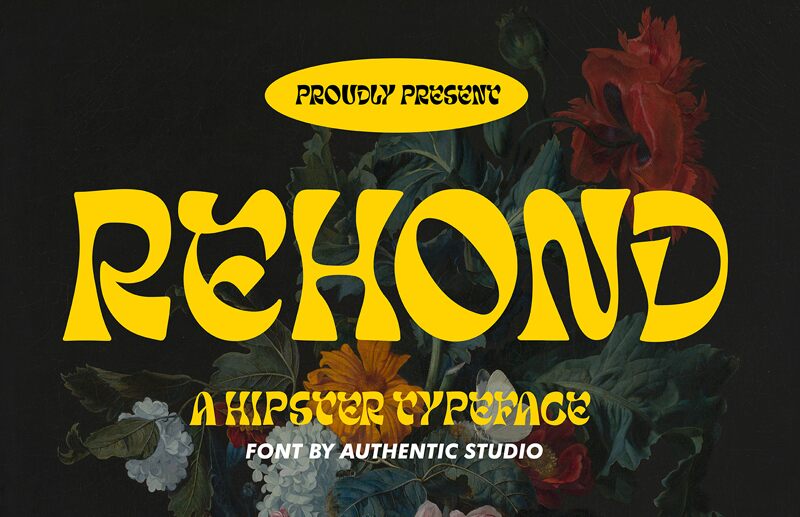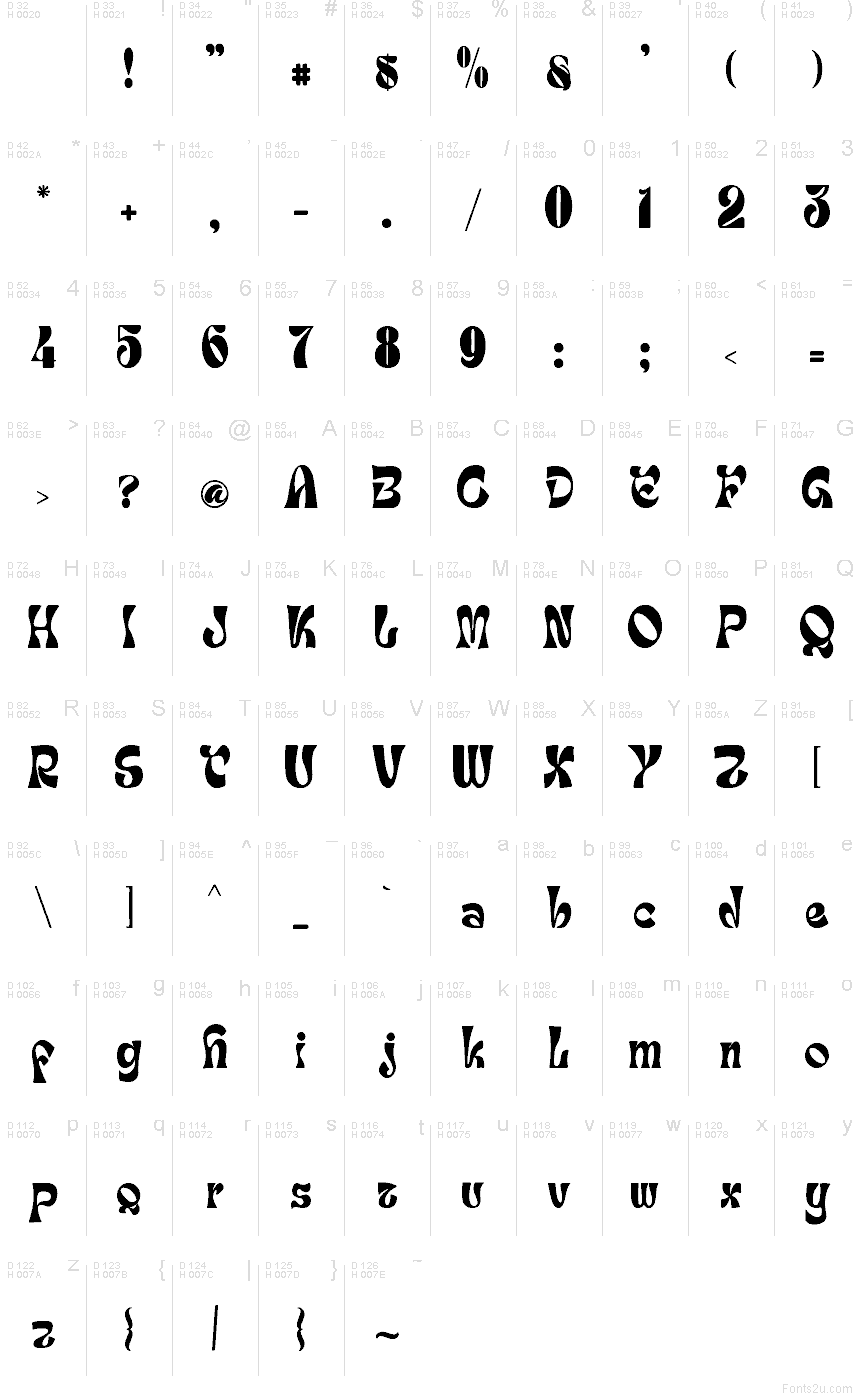
Rehond Font
Rehond Font от Faras Dina — это бесплатный грововый дисплейный шрифт с округлыми, плавными формами и теплым ретро-изгибом в очертании букв. Его формы сочетают в себе мягкие петли, разомкнутые круги и скругленные края, что придает дизайну расслабленный и декоративный ритм.
Rehond Font отлично подходит для оформления заголовков на плакатах, обложках альбомов, флаерах, ретро-брендинге, графике для соцсетей и упаковке, где нужен яркий визуальный акцент. Изогнутые формы и декоративный характер шрифта делают его идеальным выбором, когда текст должен задавать визуальное настроение макета, особенно в коротких названиях, логотипах и броских заголовках.